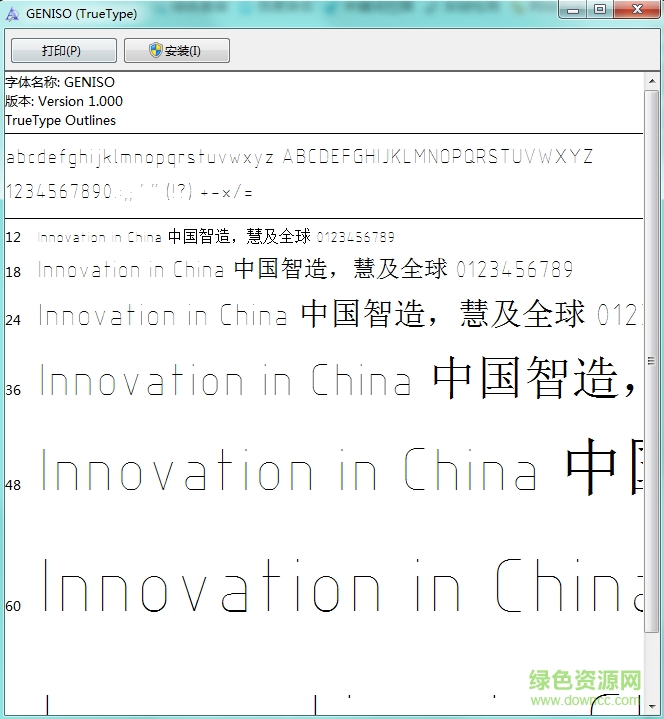
geniso字體是一款英文清淡中文濃墨的英文字體,英文輸入上線條明朗但字跡較淺,有著獨(dú)特的書寫美感,適用于商標(biāo)制作、品牌設(shè)計(jì)、廣告創(chuàng)意等諸多領(lǐng)取!
geniso支持中英文輸入,中文大方得體字跡較深,英文簡(jiǎn)約獨(dú)特痕跡偏淺,同時(shí)擁有兩種鮮明的對(duì)比,讓中文更加醒目!